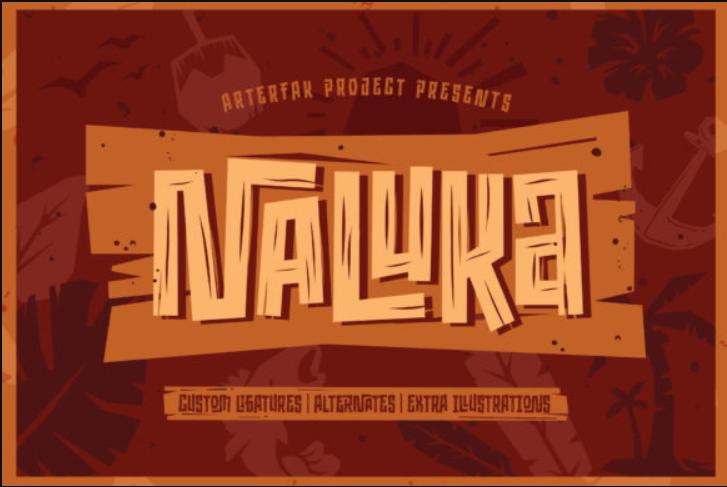
[Creativefabrica] Naluka Font (Arterfak Project)
Naluka - это крутой, толстый буквенный и мультяшный дуэт-шрифт (дингбаты и дисплей). Этот шрифт отлично подходит для детских тематических дизайнов, особенно в сочетании с яркими цветами. Naluka имеет кодировку PUA, что означает, что вы можете легко получить доступ...